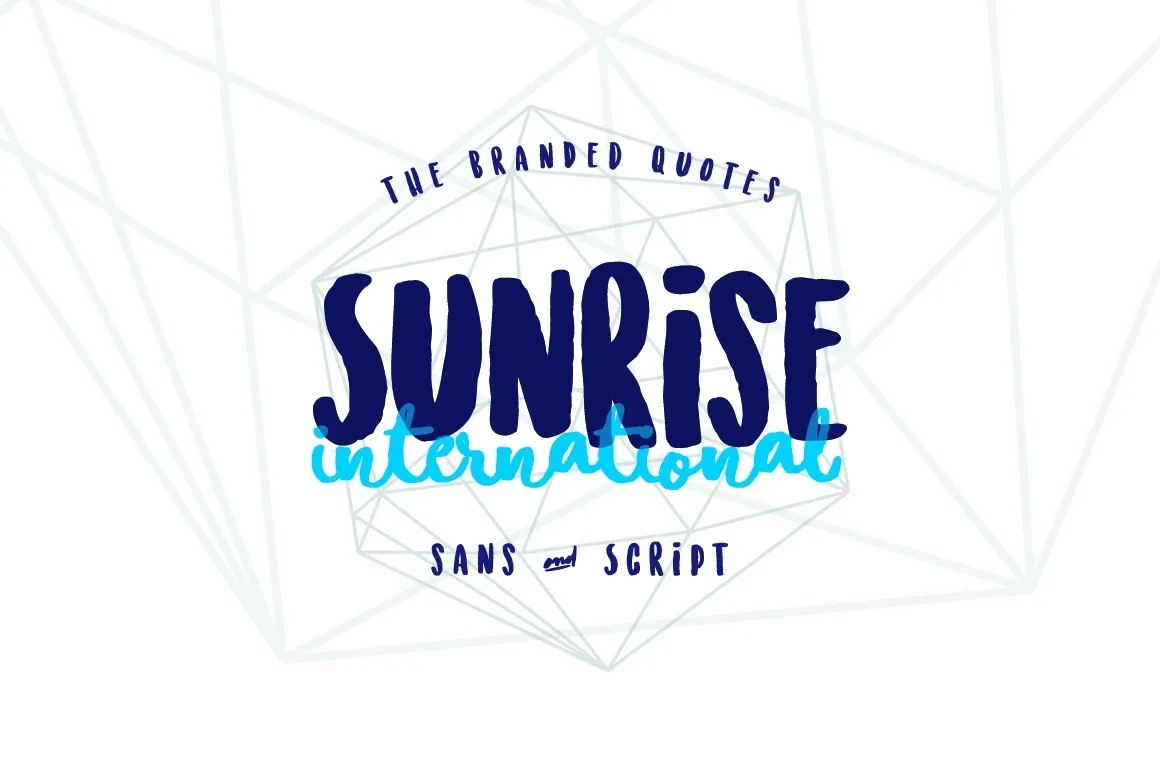
Sunrise International Font
Descubra a beleza única da Sunrise International Font, perfeita para quem busca uma letra com gestual elegante e harmoniosa. Conhecida por seu designer Hamilton, essa fonte Brush é ideal para estilos modernos e sofisticados. Perfeito para criar cartazes de alto impacto ou designs gráficos elaborados. Com seu conjunto completo de caracteres únicos, a Sunrise International Font oferece uma variedade impressionante que complementa perfeitamente as características da Internacional Script. Este Standard License garante o uso em múltiplos projetos sem necessidade de registro adicional. Adquira agora e experimente a criatividade única dessa fonte impecável.